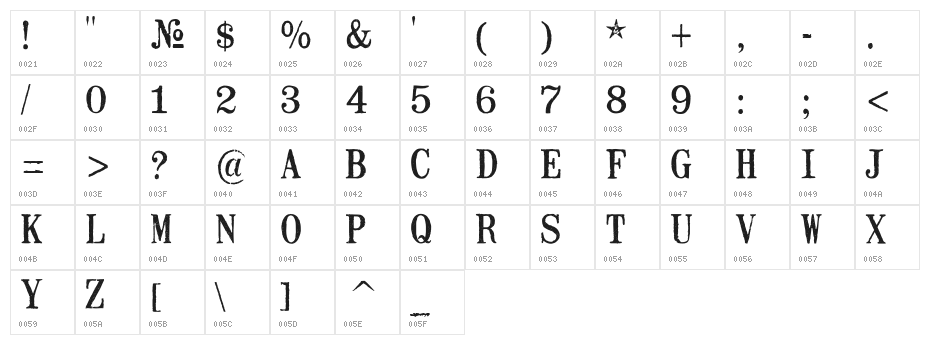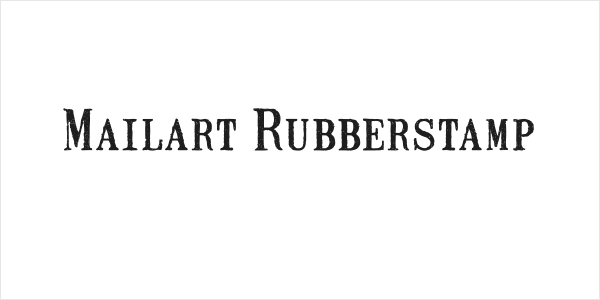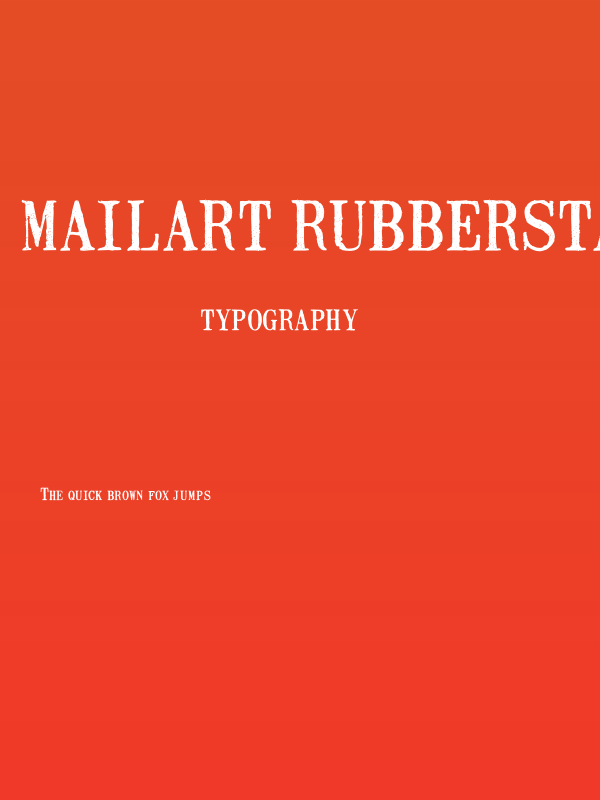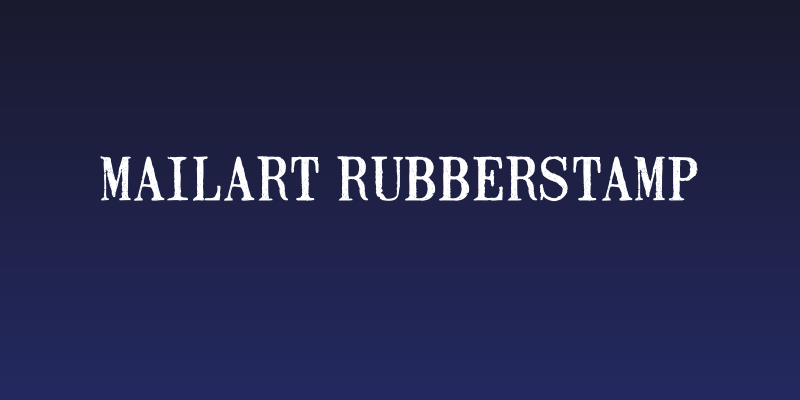
Mailart Rubberstamp Font
✎ Distorted Eroded
| Gesamtstil | Vintage |
| Vorgeschlagene Projekte | Ideal for vintage-themed designs, posters, branding, packaging, and any project that requires a retro or industrial aesthetic. |